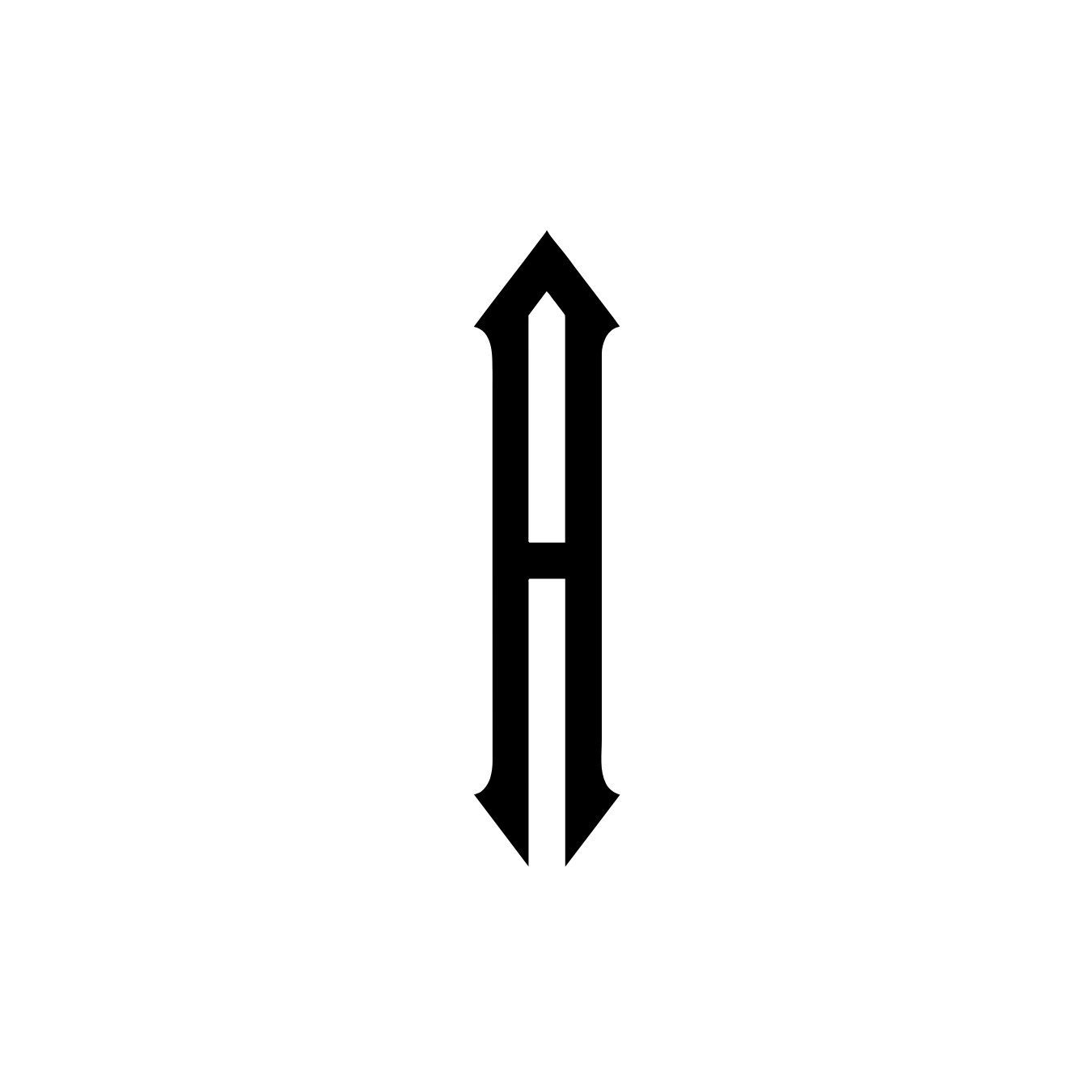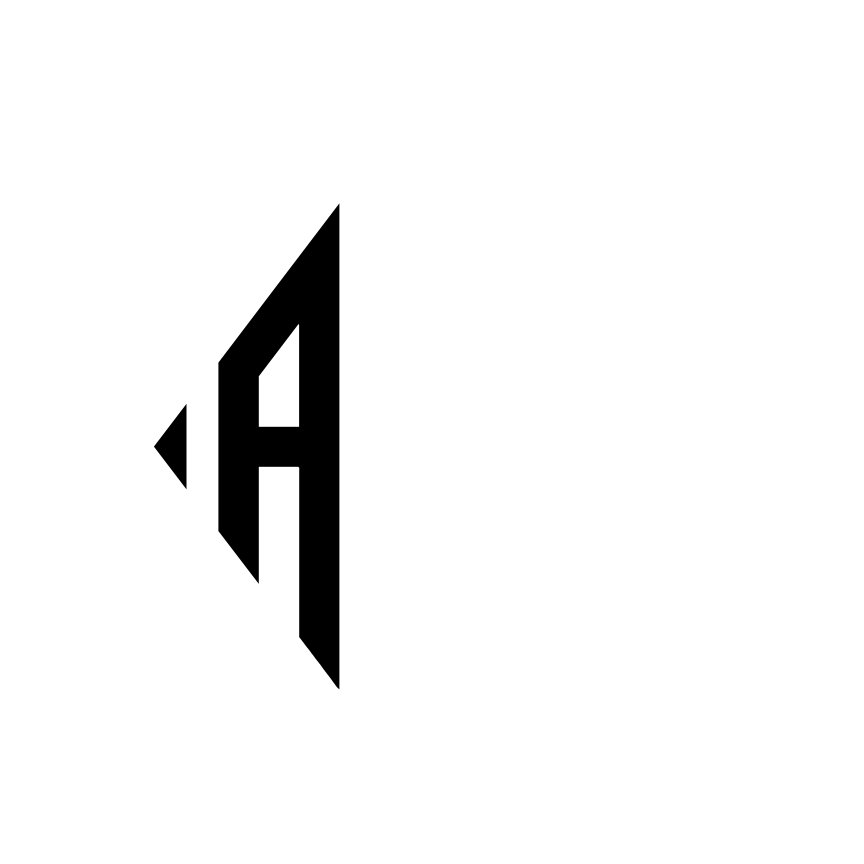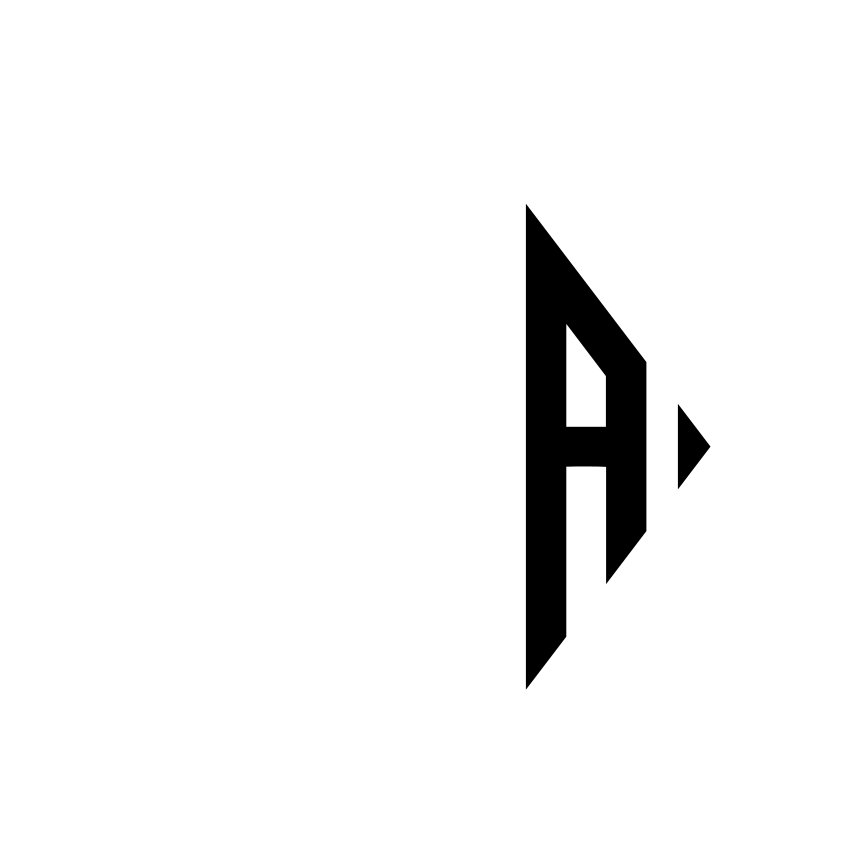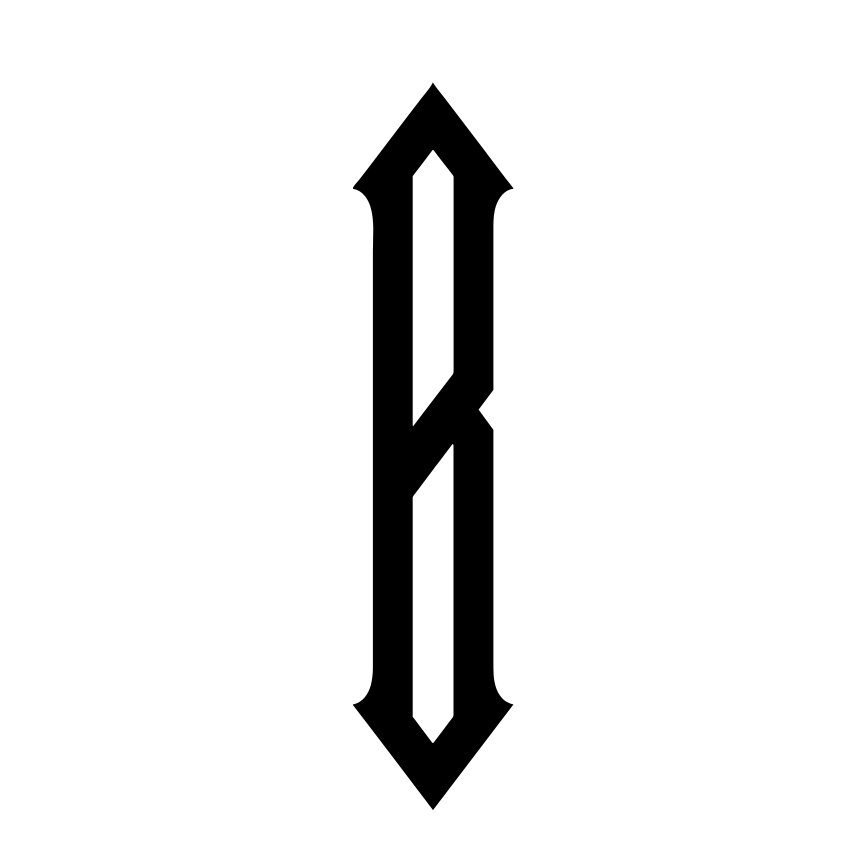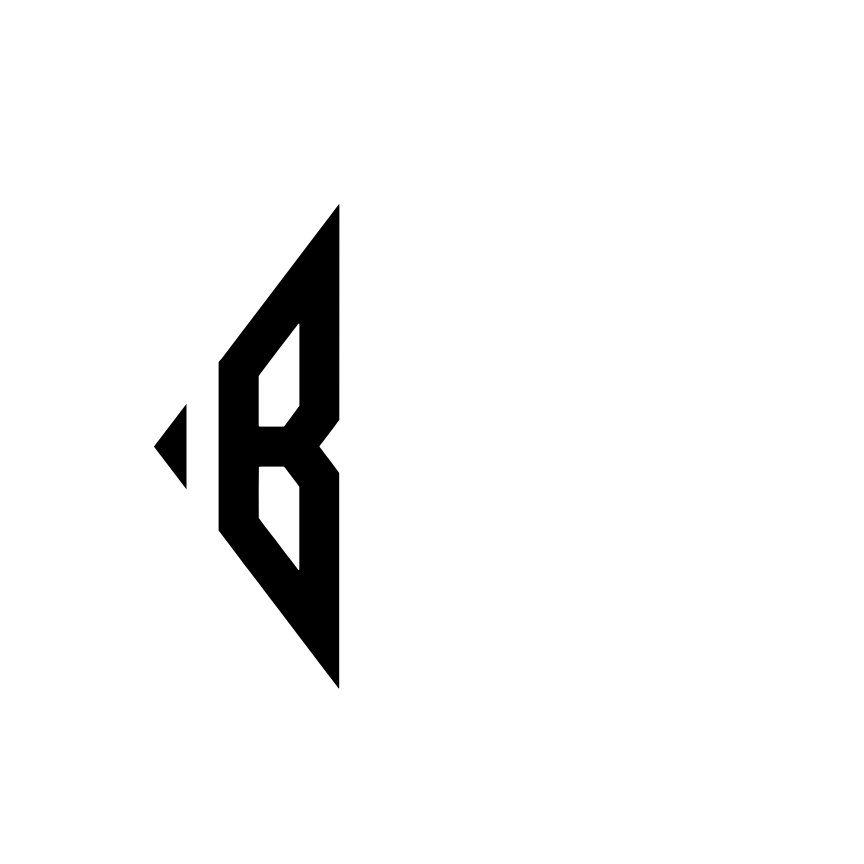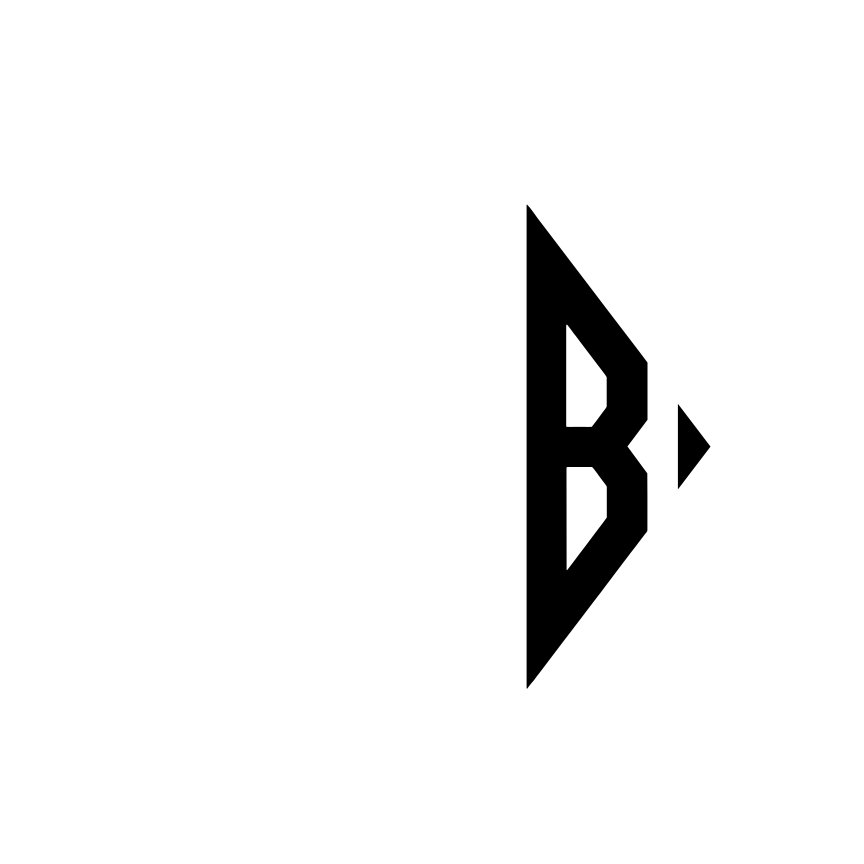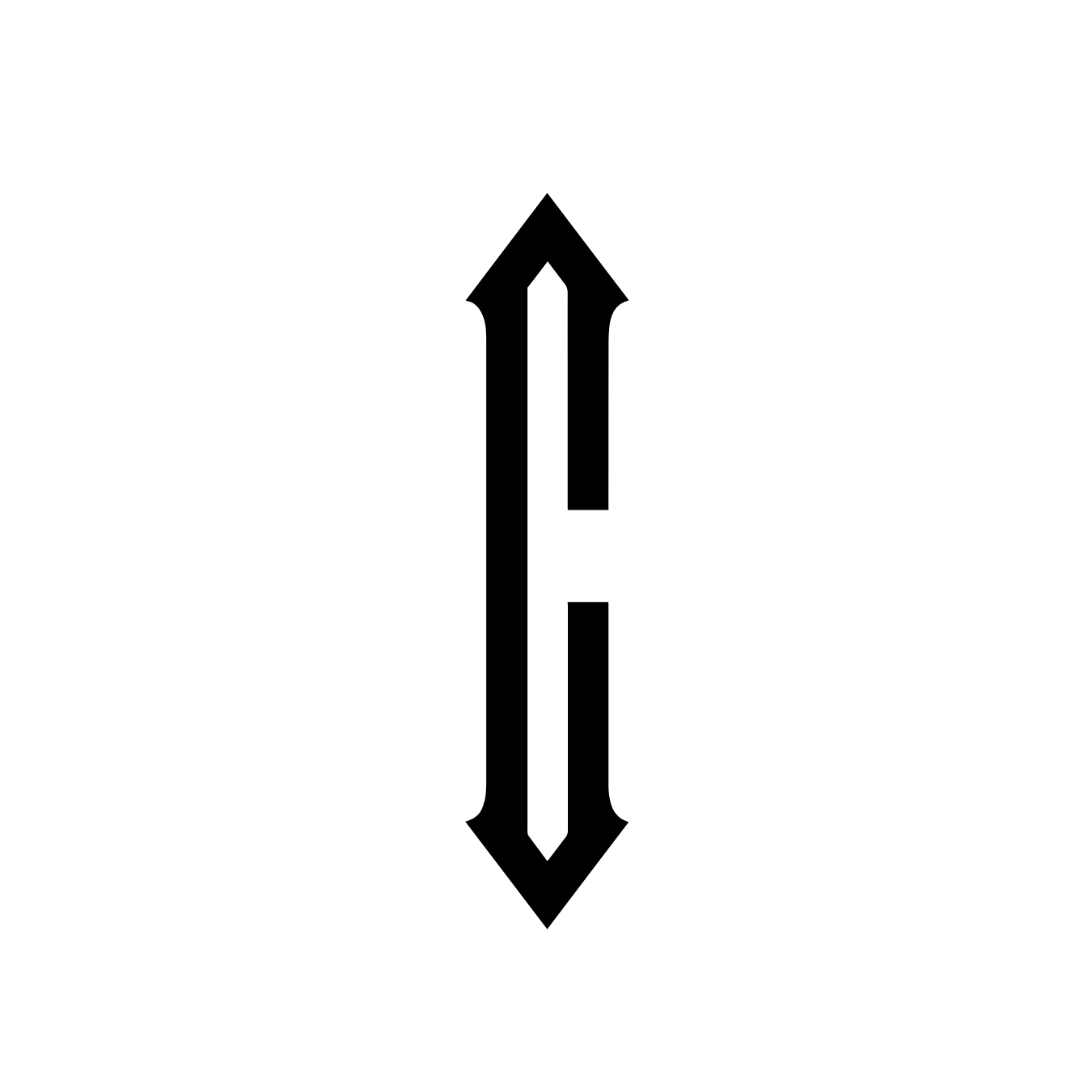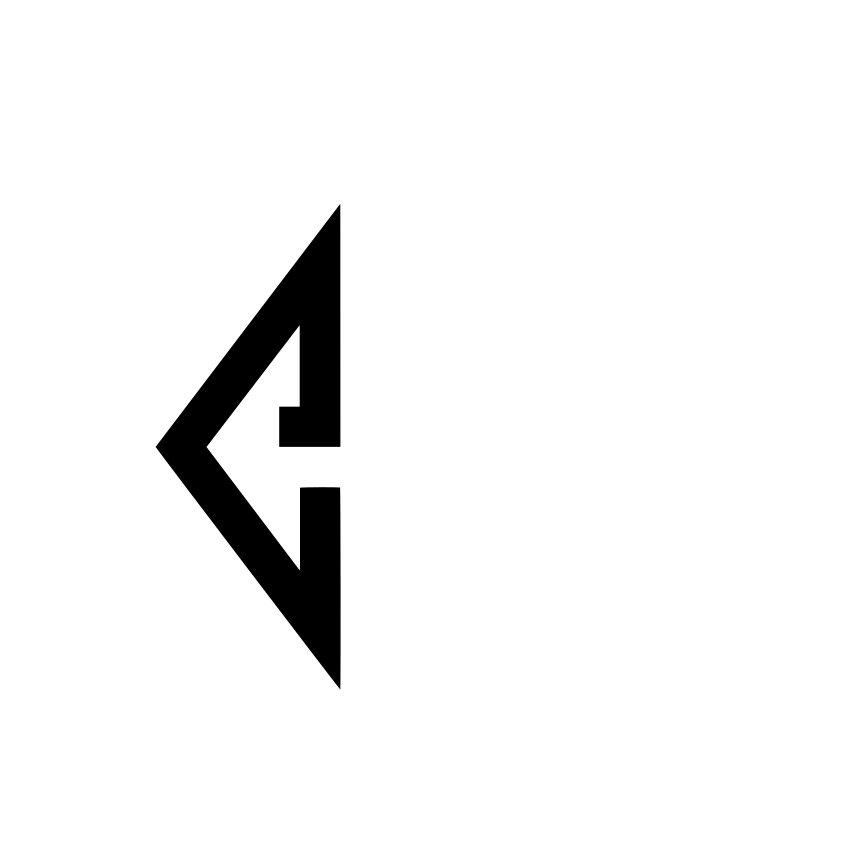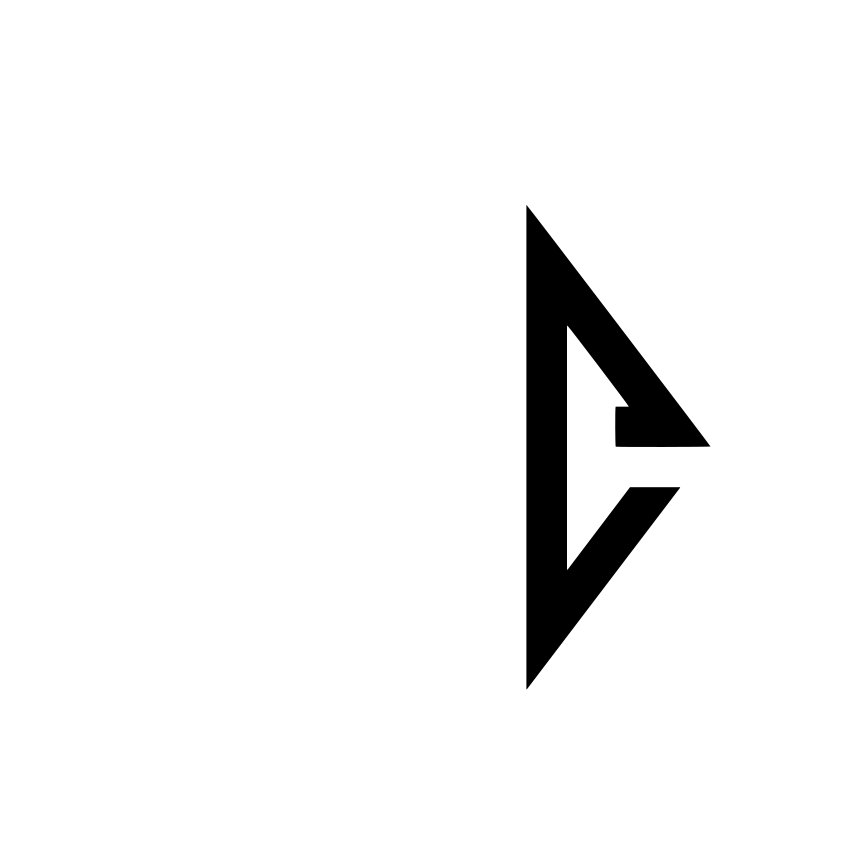
Diamond Monogramm Schriftart – Geometrisches Kristall-Alphabet mit linken, mittleren und rechten Buchstaben | Cricut-kompatibel
• Die Diamond Monogramm Schriftart ist eine markante geometrische Monogramm-Schrift, inspiriert von Kristall- und Diamantformen. Jeder Grossbuchstabe besitzt klare, symmetrische Linien, die besonders in dreibuchstabigen Monogramm-Layouts eine starke und strukturierte Wirkung erzeugen.
• Jeder Buchstabe ist in drei Varianten verfügbar: links, Mitte und rechts. Dadurch lassen sich ausgewogene Monogramm-Designs erstellen, bei denen der mittlere Buchstabe vertikal betont wird, während die seitlichen Buchstaben ihn mit passenden, angewinkelten Formen einrahmen.
• Der klare Kristallstil eignet sich besonders gut für personalisierte Bastelprojekte wie Trinkglas-Aufkleber, Hochzeitsdekorationen, individuelle Geschenke, Wanddesigns, Etiketten und dekorative Schriftzüge.
• Die Schrift enthält ausschliesslich Grossbuchstaben, wobei jeder Buchstabe in einer linken, mittleren und rechten Version vorhanden ist, um strukturierte und harmonische Monogramm-Designs zu erstellen.